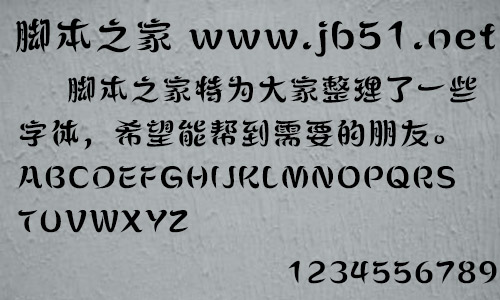
方正飛躍體簡(jiǎn)ExtraBold是由方正字庫(kù)最新開(kāi)發(fā)的一款中文藝術(shù)字體,又可以稱為方正飛躍體簡(jiǎn)大字體,字體帶有非?;钴S的氣氛,還想每一筆都忍不住想要跳起來(lái),字體整體具有很強(qiáng)的辨識(shí)度,適合應(yīng)用于藝術(shù)設(shè)計(jì)、平面宣傳設(shè)計(jì)、網(wǎng)頁(yè)設(shè)計(jì),書(shū)法字貼等領(lǐng)域,需要的朋友可以前來(lái)本站下載。